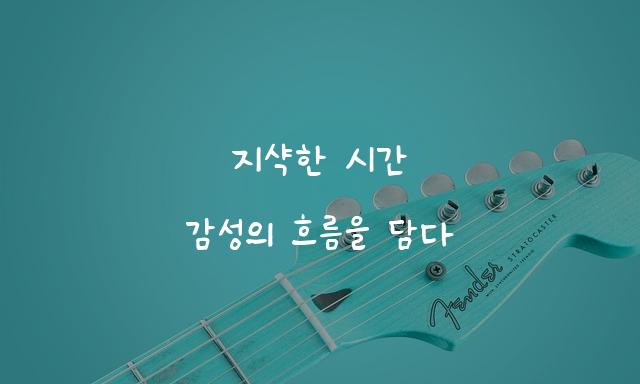
세구세구체는 JellyBrick에서 제작한 독특한 삐뚤빼뚤한 감성의 폰트입니다. 특이한 형태와 직관적인 디자인으로 시선을 끕니다.
어린이 책, 인사말 카드, 소셜 미디어 등에서 자주 활용되며, 효과적인 메시지 전달에 적합합니다.
이 폰트는 음식/식음료, 라이프스타일, 유아/가족 분야에 잘 어울리며,
친근한, 귀여운, 재미있는 느낌을 담고 있는 것이 특징입니다.
이 폰트와 유사한 폰트로는 손글씨체, 구슬체, 낙서체 등이 있어요. 함께 비교해 보시면 좋습니다!